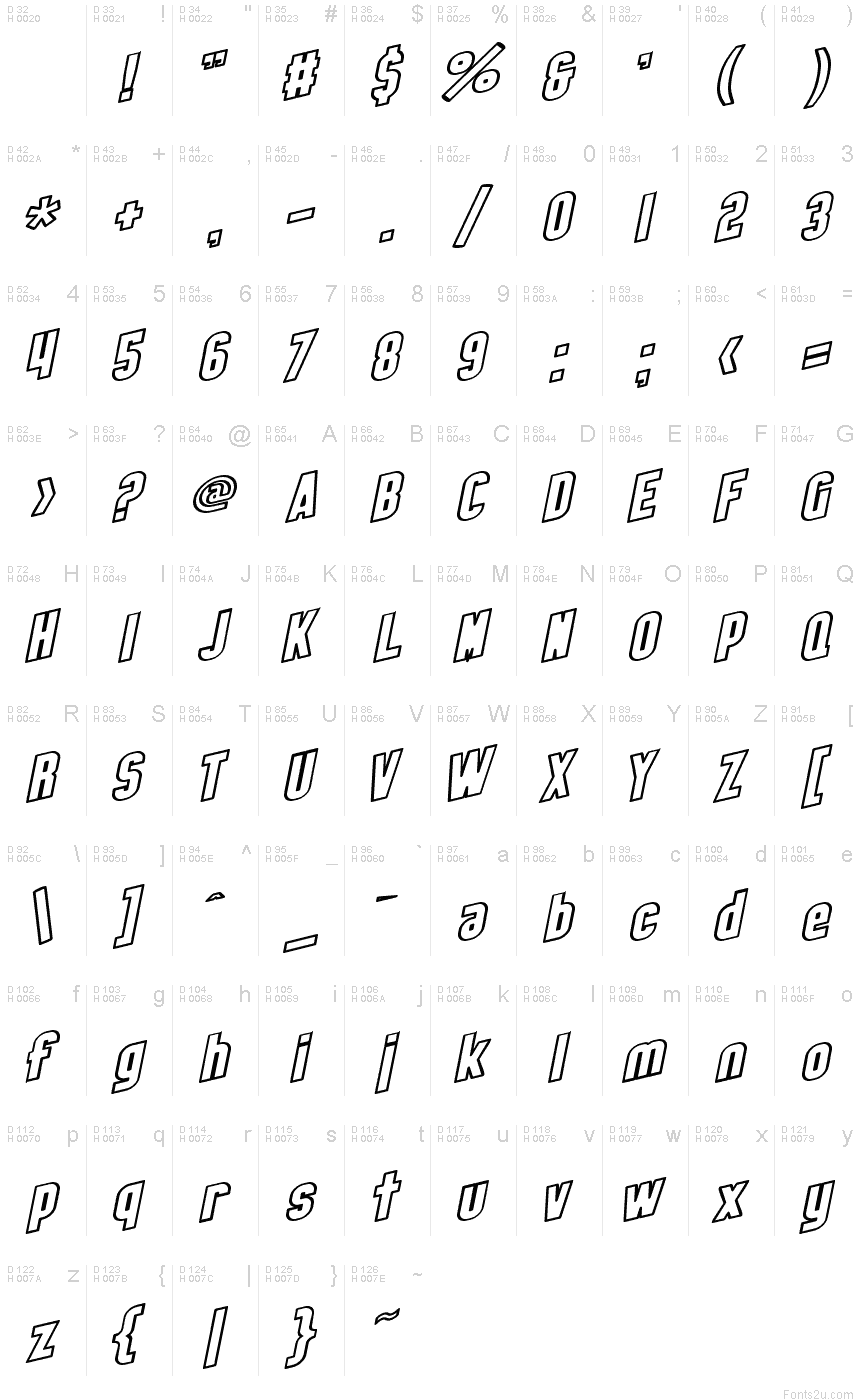
SF Obliquities Outline Bold od ShyFoundry to darmowy, konturowy krój pisma typu display, charakteryzujący się szybkim, komiksowym pochyleniem. Litery są mocno pochylone i wyglądają, jakby zostały wycięte z grubych, czarnych linii; połączenie zaokrąglonych łuków z ostrymi, klinowatymi kątami nadaje całości naładowany energią, sportowy rytm.
Dzięki temu czcionka ta jest naturalnym wyborem do nagłówków na plakatach, grafiki w grach, okładek, ulotek eventowych czy szkiców logo, gdzie ruch liczy się bardziej niż gładkość. Jako darmowy font, świetnie sprawdza się również w planszach tytułowych, w brandingu streamerów czy krótkich tekstach na gadżety, ponieważ otwarte wnętrze liter i gruby obrys sprawiają, że styl pozostaje wyrazisty nawet przy kilku słowach.
SF Obliquities Outline
ShyFoundry
Derek Vogelpohl